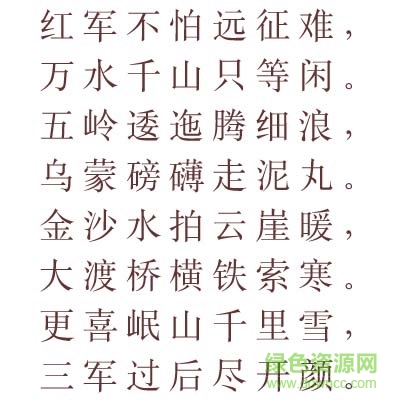
長(zhǎng)城宋體是一款很標(biāo)準(zhǔn)的宋體字體,整個(gè)字形的特點(diǎn)也和宋體差不多,豎粗橫細(xì),該字體很多地方都可以使用。適用于多種場(chǎng)合,是每個(gè)人都會(huì)擁有的一款字體,趕快來(lái)綠色資源網(wǎng)下載體驗(yàn)吧!